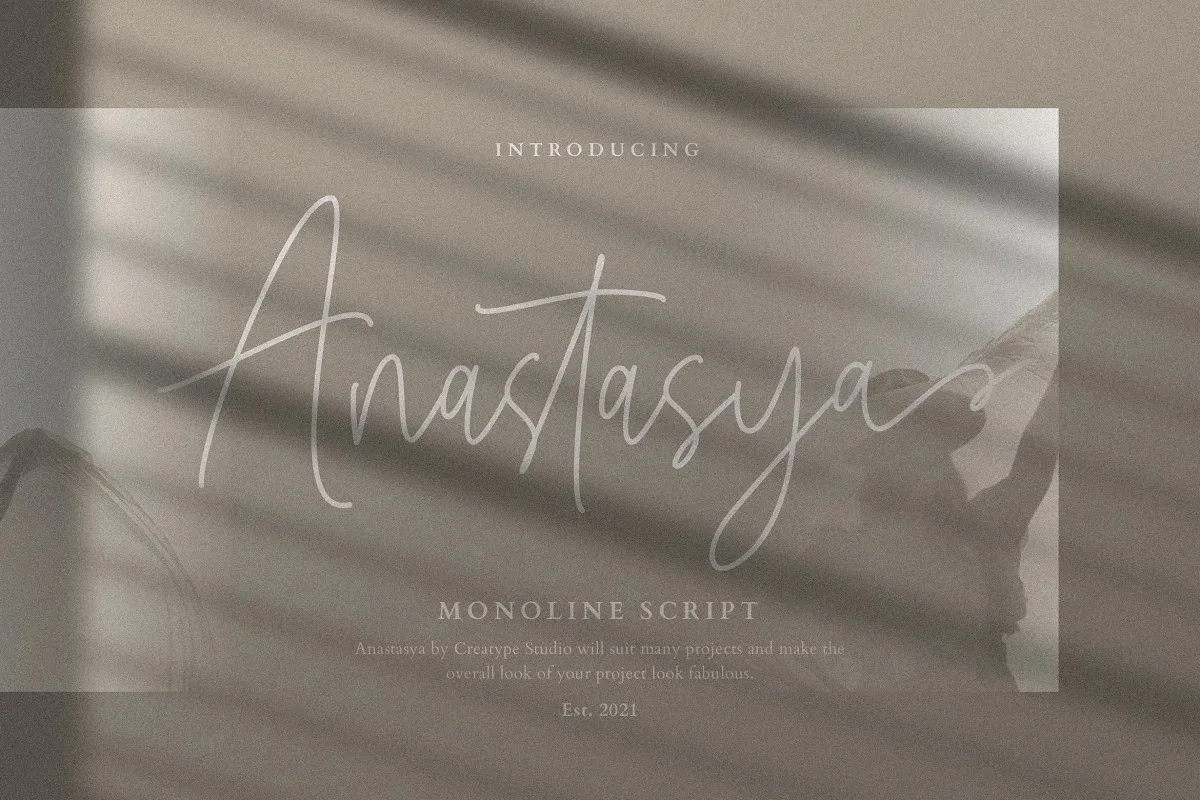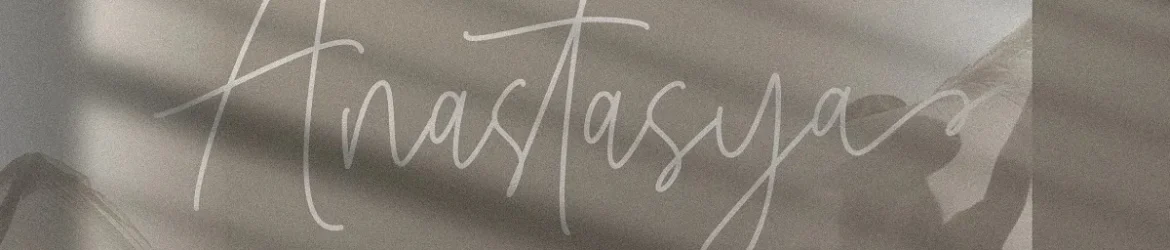
Anastasya Font é uma elegante tipografia script produzida pela Creatype Studio. Com um estilo limpo, fininho e suave, esta fonte será perfeita para qualquer projeto de design que você deseje incorporar. Ideal para trabalhos de marca, logotipos, designs de casamentos, posts nas redes sociais, anúncios, embalagens de produtos, criação de produtos, rótulos, fotografia e até mesmo marcas ou papelaria, Anastasya traz um toque autêntico da escrita à sua arte. Este script font é perfeito para qualquer projeto que precise de uma pitada de charme do mundo das letras. Não importa o tipo de trabalho em que você esteja trabalhando: seu próximo design pode se beneficiar dos encantos delicados e sofisticados desta fonte da 99designs.